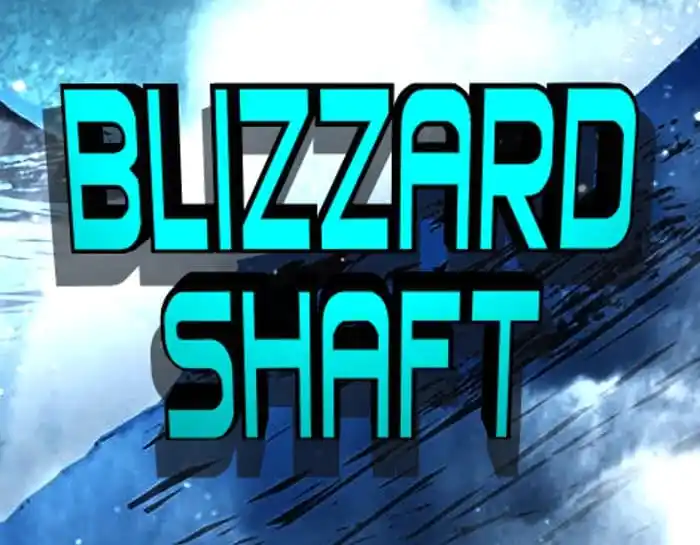
Blizzard Shaft Display Font
A Blizzard Shaft Display Font é uma combinação única de estilo moderno e elegância, criada para entregar texturas impressionantes e características distintivas que não são encontradas nas demais fuentes disponíveis. Com uma ampla gama de 36 versões, incluindo regular, negrita, itálico, super-itálico, semicarbonado e estendido, a Blizzard Shaft Display oferece um conjunto impecável para personalizar desde o simples logotipo até a capa de um livro. Especialmente adequada para uso em design gráfico moderno, como arquitetura digital, branding, embalagens, arte digital ou publicidade online. A Blizzard Shaft Display é perfeitamente adaptável a uma variedade de ambientes, criando texturas interessantes e profundas que podem ser usadas tanto no layout tradicional quanto em design 3D, tornando-a uma excelente escolha para qualquer aplicação onde um forte estilo de fonte seja desejado.